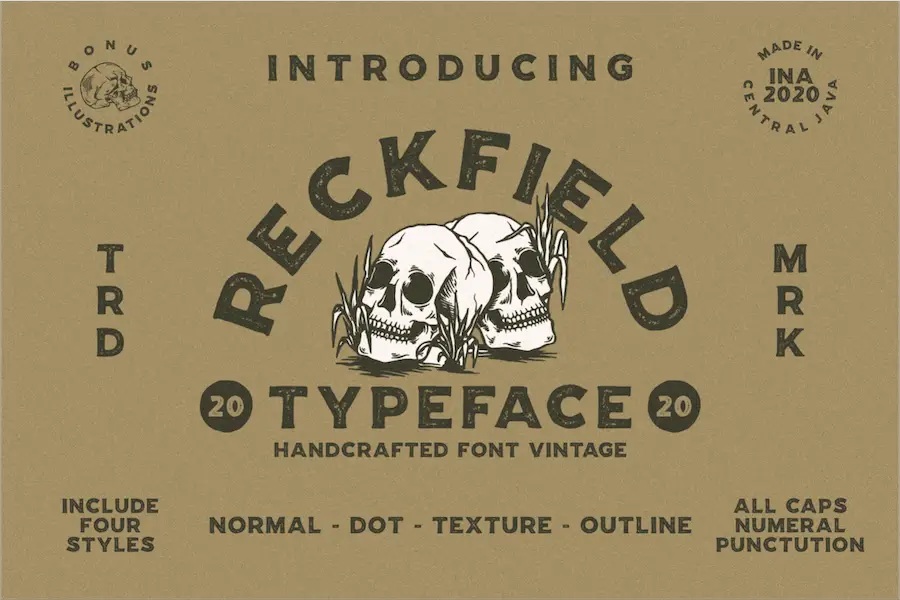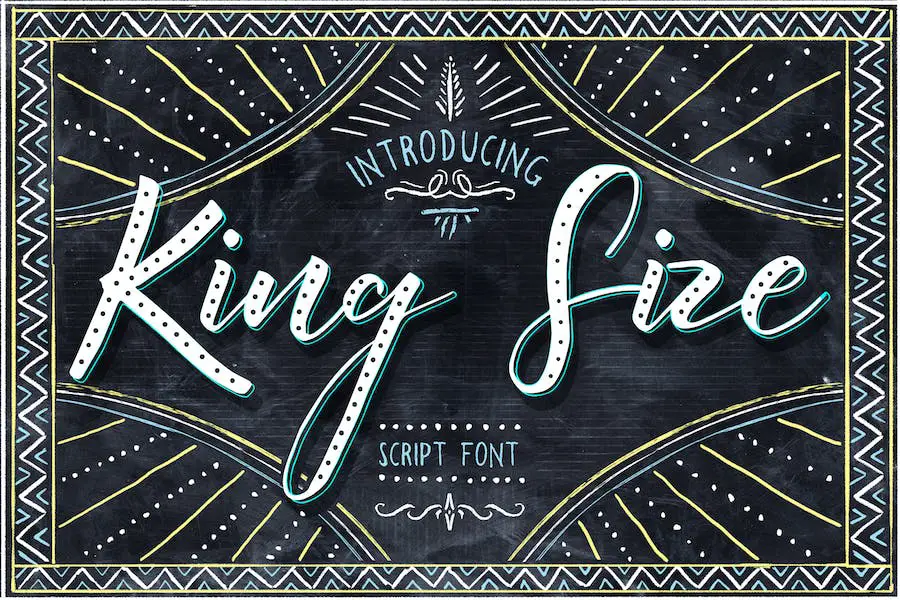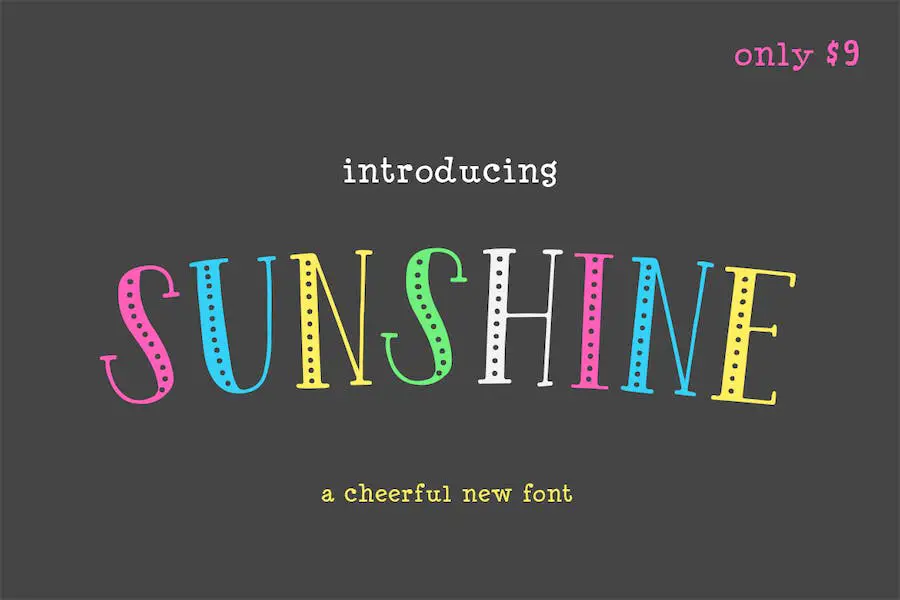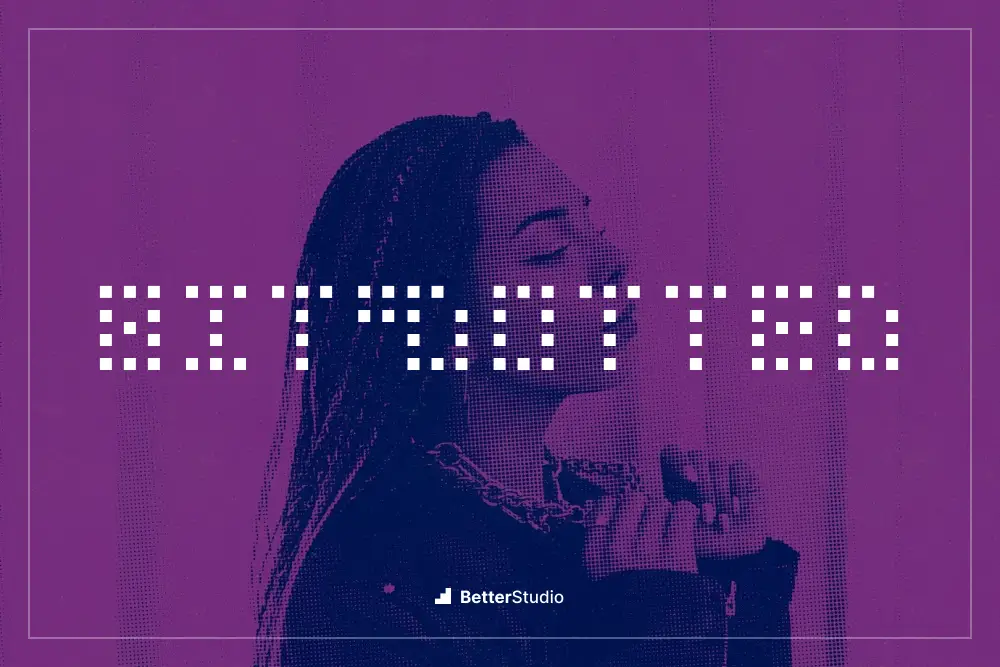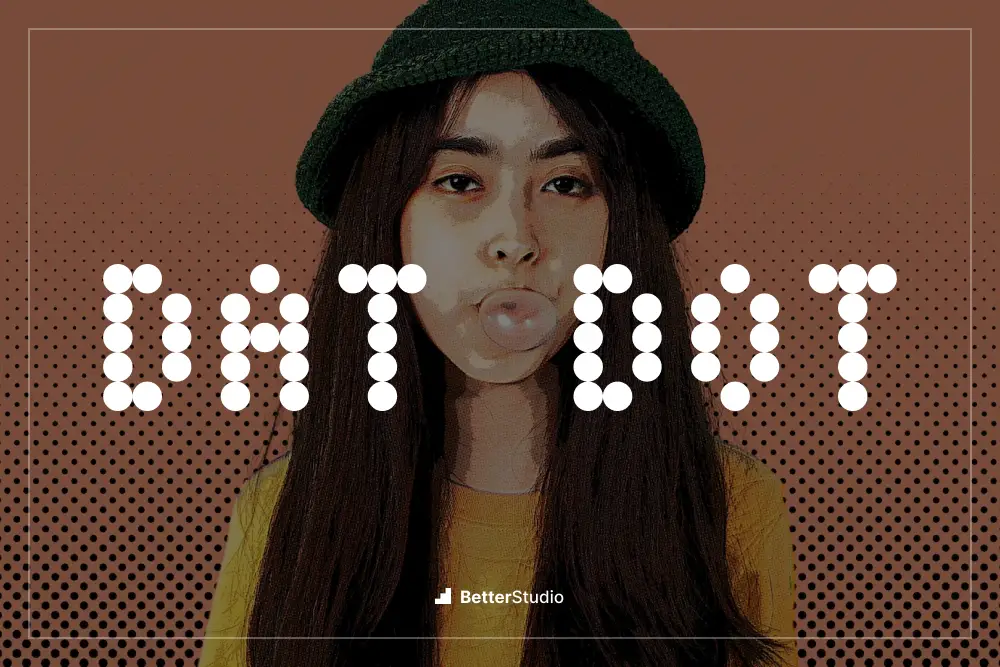
În această postare pe blog, vom explora cele mai bune 15 fonturi punctate din 2023, atât opțiuni gratuite, cât și opțiuni premium, pentru a vă îmbunătăți eforturile creative.
S-ar putea să vă întrebați de ce sunt fonturile punctate atât de importante pentru designerii grafici. Ei bine, aceste fonturi unice oferă un element jucăuș și atrăgător oricărui design.
Indiferent dacă creați un afiș, un logo sau un site web, încorporarea unui font punctat poate adăuga o notă de creativitate și capriciu muncii dvs.
În acest articol, vă vom prezenta o listă atent îngrijită a celor mai bune 15 fonturi punctate, prezentându-le caracteristicile, versatilitatea și impactul general asupra designului.
Vom discuta despre disponibilitatea acestora ca opțiuni gratuite sau premium, oferindu-vă flexibilitatea de a alege în funcție de cerințele și bugetul dumneavoastră specifice. Așa că pregătește-te să descoperi niște fonturi punctate uimitoare care îți vor transforma desenele în opere de artă!
Cele mai bune fonturi cu puncte premium
Sunteți designer grafic în căutarea fontului perfect pentru a îmbunătăți designul proiectului dvs.? Nu mai căuta! În această secțiune, vom prezenta cele mai bune fonturi premium punctate disponibile pe piață.
Nu ratați ocazia de a explora și descoperi aceste fonturi incredibile care vă vor duce design-urile la nivelul următor. Aruncă o privire la produsele prezentate în acest articol și lasă-ți creativitatea să se avânte!
Zbor
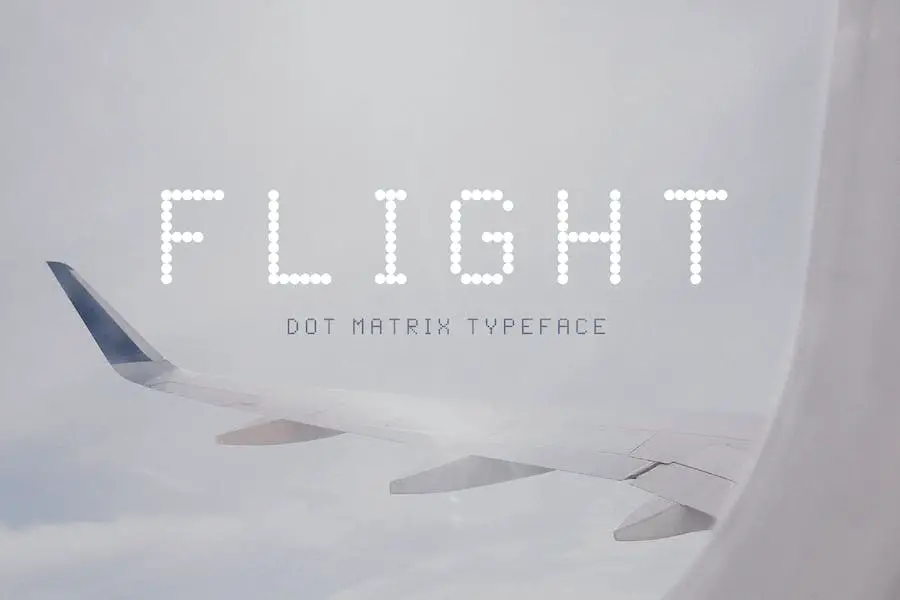
Flight este un tip de liter uimitor care se inspiră din imprimantele matriceale care se găsesc încă în aeroporturi la nivel global. Este perfect pentru diverse scopuri de design, inclusiv editoriale, branding, postere și web design.
Caracteristica unică a fontului sunt punctele sale mici bazate pe grilă, care creează forme de litere frumos lizibile.
Cu Flight, poți aduce o notă de nostalgie proiectelor tale, păstrând în același timp un aspect modern și profesional. Versatilitatea sa îl face potrivit pentru o gamă largă de industrii, inclusiv publicarea, designul logo-ului, dezvoltarea de software, jocurile și chiar panourile publicitare.
Salvadorul
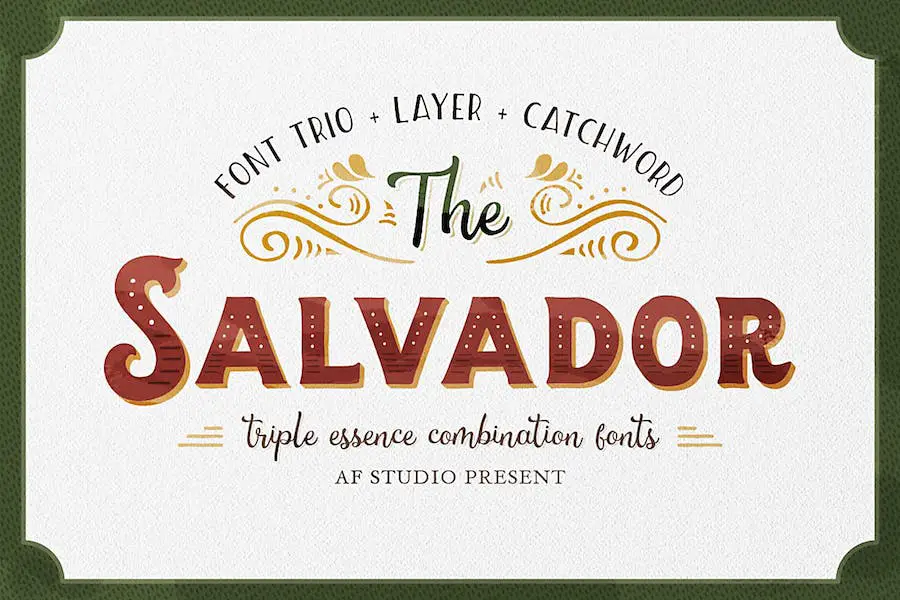
Salvador este o combinație trio de fonturi care se inspiră din stilul unic de tip handlettering al unui artist de litere talentat. Cu variația sa Condensed, include chiar și cuvinte cheie pentru a îndeplini toate nevoile dvs. de combinație de fonturi.
Pentru a utiliza acest font, introduceți pur și simplu cuvântul dorit cu caractere de subliniere în jurul acestuia, cum ar fi _cuvânt_. Versiunea Serif a lui Salvador oferă 4 straturi: bază, umbră, în linie și în linie punctată.
Opțiunile Inline și Dotted Inline oferă un stil similar, astfel încât să puteți alege oricare dintre ele se potrivește cel mai bine proiectului dvs. Cu straturile sale elegante și opțiunile versatile, Salvador va îmbunătăți cu siguranță designul proiectelor dvs. cu o notă de eleganță.
BORSE
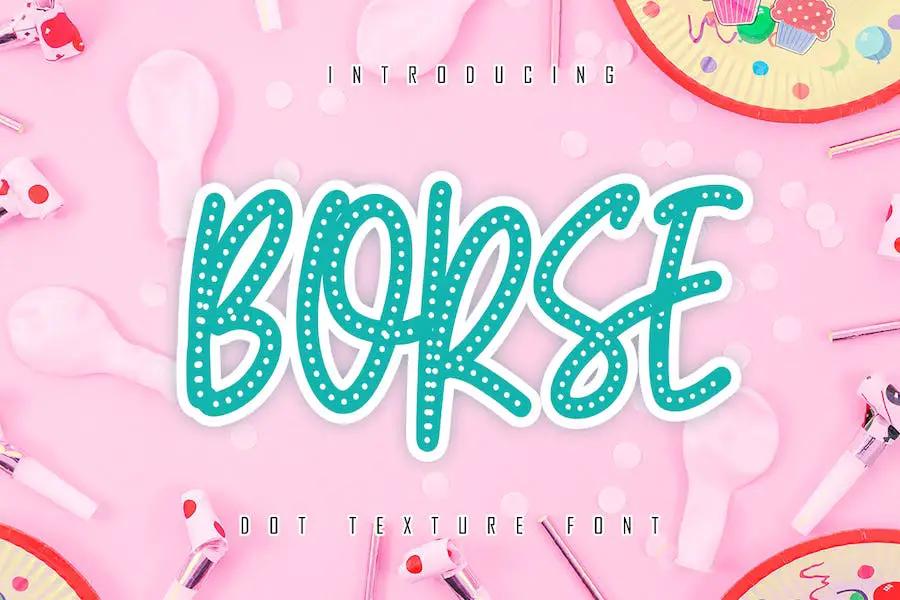
Acest font se inspiră din caligrafia modernă, creând o temă distractivă și jucăușă care va atrage cu siguranță atenția.
Cu BORSE, puteți crea modele atrăgătoare pentru diverse scopuri, de la caligrafie serif la postere, proiecte legate de alimente, nunți și branding. Versatilitatea fontului îl face potrivit pentru o gamă largă de proiecte de design, permițându-vă să vă eliberați creativitatea și să vă aduceți ideile la viață.
Indiferent dacă proiectați pentru Google, Adobe, Word, Canva, Circuit, Figma sau chiar pentru tatuaje sau postări pe Instagram, BORSE vă acoperă. Este compatibil cu diverse software și platforme de proiectare, ceea ce facilitează integrarea în fluxul de lucru existent.
Inimă sălbatică
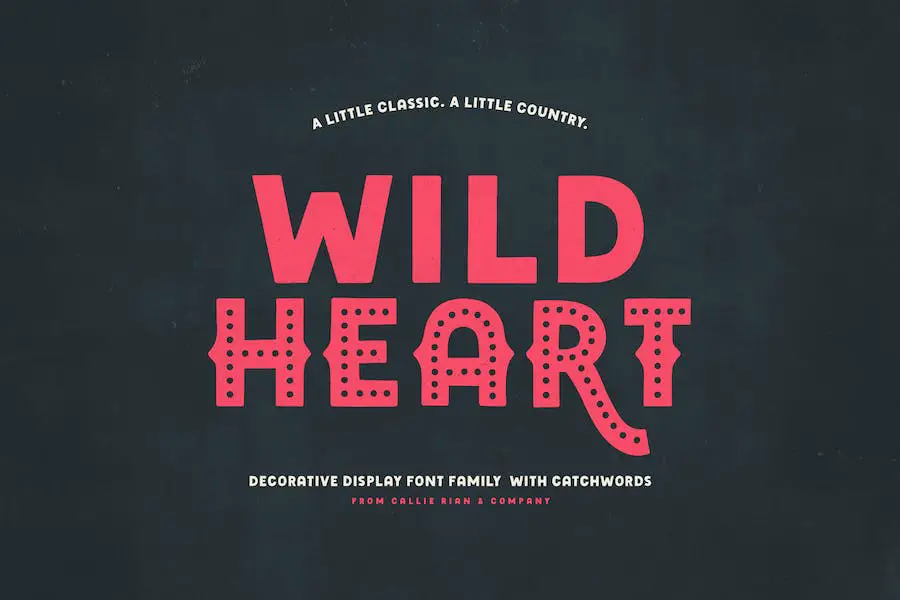
Wild Heart este o familie versatilă de fonturi sans serif, care oferă șase versiuni decorative, împreună cu un font dingbat și cuprinzător. Include, de asemenea, un fișier de textură care vă permite să adăugați un efect grungy tipografiei dvs. în Photoshop.
Cu versiunea punctată sau conturată, puteți obține un aspect retro. Dacă te simți un pic de țară, versiunea cu pinteni este perfectă. Și pentru o atmosferă mai tradițională, poți rămâne cu simplitatea Wildheart Regular.
Acest font este o alegere excelentă pentru o gamă largă de proiecte, de la logo-uri la felicitări la autocolante și nu numai. Așa că dezlănțuiește-ți creativitatea și dă-ți design-urilor o notă de sălbăticie cu Wild Heart.
Visage Polka Dot
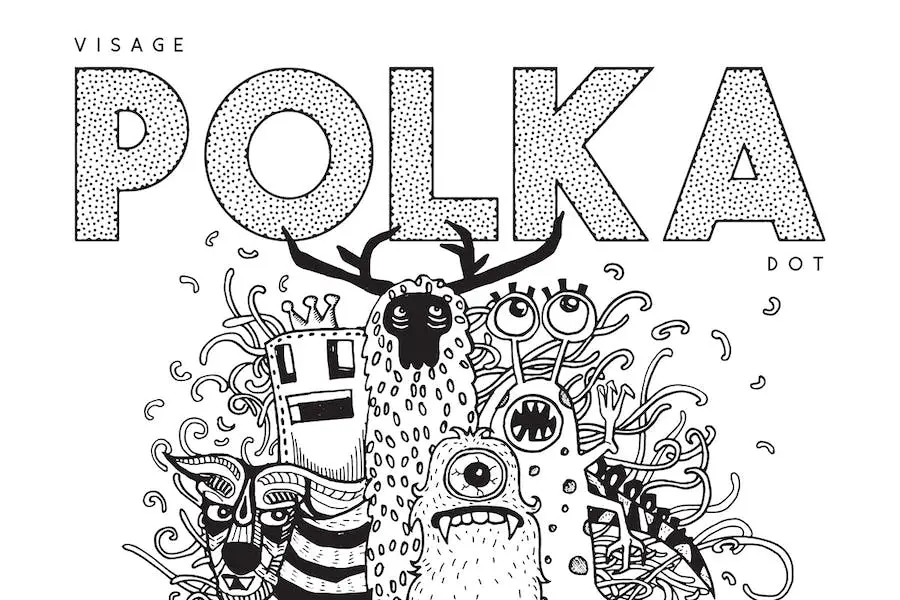
Visage Polka Dot este fontul perfect pentru designerii grafici care doresc să-și îmbunătățească proiectele cu un plus de jucăuș. Cu designul său unic cu buline, acest font adaugă o atmosferă distractivă și prietenoasă oricărui titlu mare.